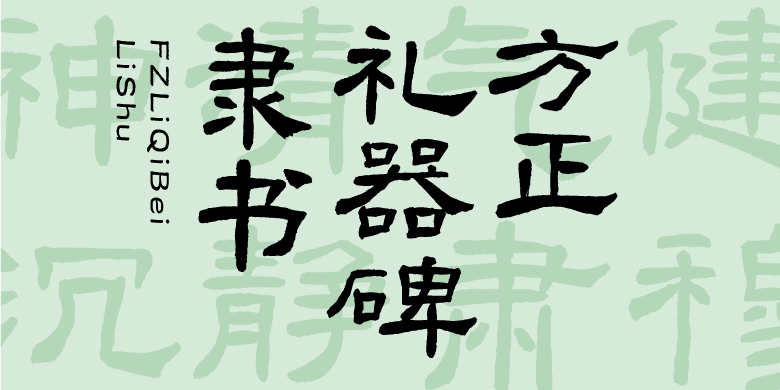
方正礼器碑隶书
方正礼器碑隶书,这款字体结构工整、笔画清晰,兼顾美观与易读性,适用于标题、正文、海报、包装、LOGO 等多种场景。字形优雅稳定,风格百搭耐看,适配日常排版与创意设计,让文字呈现更舒适、更具质感。方正礼器碑隶书一笔一画,皆是细节,以均衡的比例、流畅的线条打造舒适视觉体验,字形端正大气,风格简约现代。无论是商业设计、品牌宣传还是日常排版,都能轻松驾驭,让文字更有格调与力量。方正礼器碑隶书字体下载。
《礼器碑》的笔画富于变化,线条凝练而不失流动,秀雅中又灵动多变。结体紧密、笔画开张舒展,清刚而不乏苍劲,严谨而不乏自由,可谓静中寓动,变化之中见统一,显得非常之潇洒灵动。整体神清气健,沉静肃穆,典雅秀丽,清超绝尘,清刚之气充溢纸面。清虚灵动中透着空灵洒脱,格调高古中洋溢着清新典雅。意定神闲,举止淡然,宛若翩翩君子庄重但不失活泼,儒雅却不乏严厉。